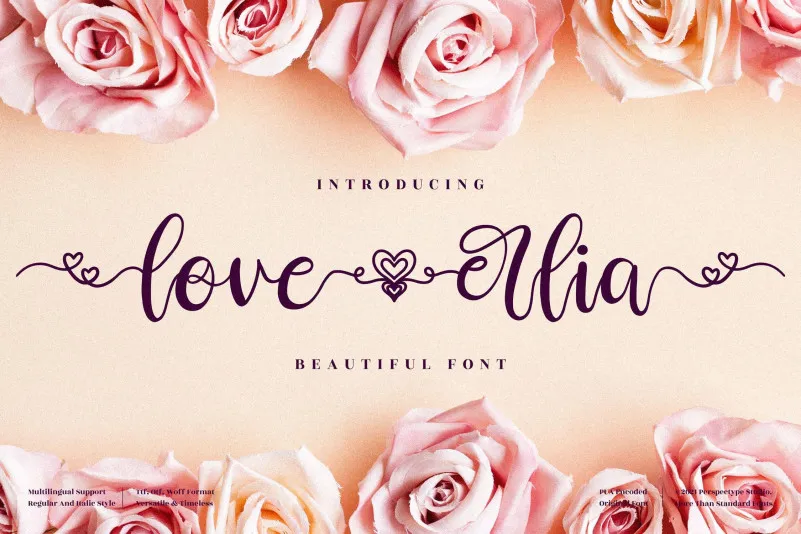
Esta é uma linda fonte tipo script com um tema amor e natureza. Ela é simples e muito fácil de usar, tornando-se extremamente bonita quando misturada com suas designs diversos para a criação manual. Esta font possui PUA (Unicode Private Use Area) que significa você pode acessar facilmente todos os símbolos e desenhos alternativos sem problemas. Esta elegante font é perfeita para quem busca uma solução de tipografia ideal, combinando delicadeza com simplicidade. Ela se encaixa perfeitamente em diversos projetos de crafts, desde pequenos cartões personalizados até grandes obras de arte digitais. Seja você um amante do design gráfico ou simplesmente alguém que aprecia uma boa fonte para seus projetos, esta script font é definitivamente para você. Não importa qual projeto está trabalhando no momento, essa font será uma ótima adição, oferecendo personalidade e elegância ao seu trabalho. O tema amor e natureza combina perfeitamente com diversos estilos de design, tornando a Love Erlia Font uma opção versátil para designers gráficos.